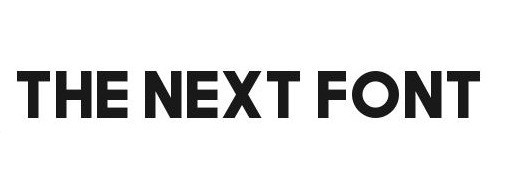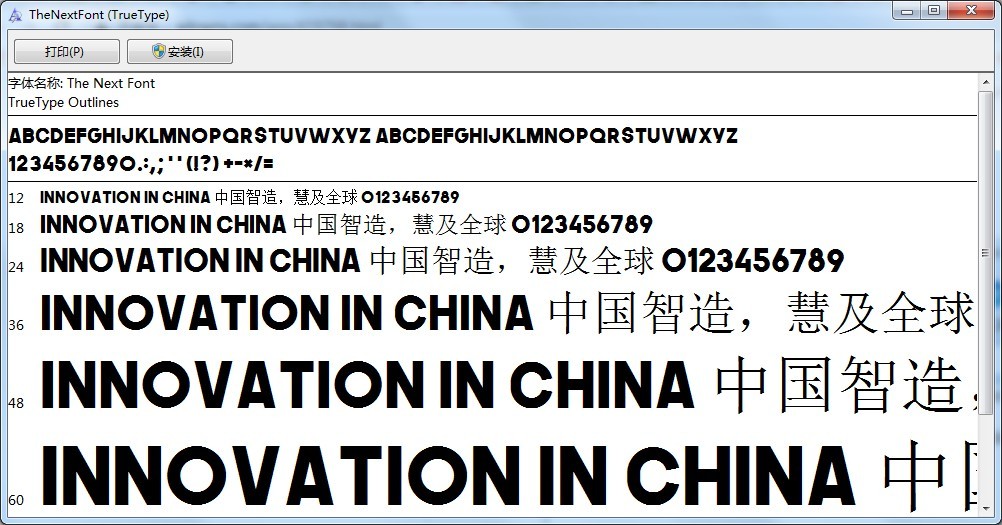
the next font
the next font当你需要粗行英文字体时就可以借助该字体包来帮助解决相关的字体样式问题,安装方法和其他ttf字体类似,需要把字体下载后在ps或是美图软件上即可使用,有需要的用户可以来下载了解更多。
the next ttf介绍
the next字形的整体效果非常好。它可以应用于文本装饰,信息显示,数据制作,网页设计,雕刻,装饰设计,计算艺术设计,视觉设计,字帖和其他法律应用场景。
the next font